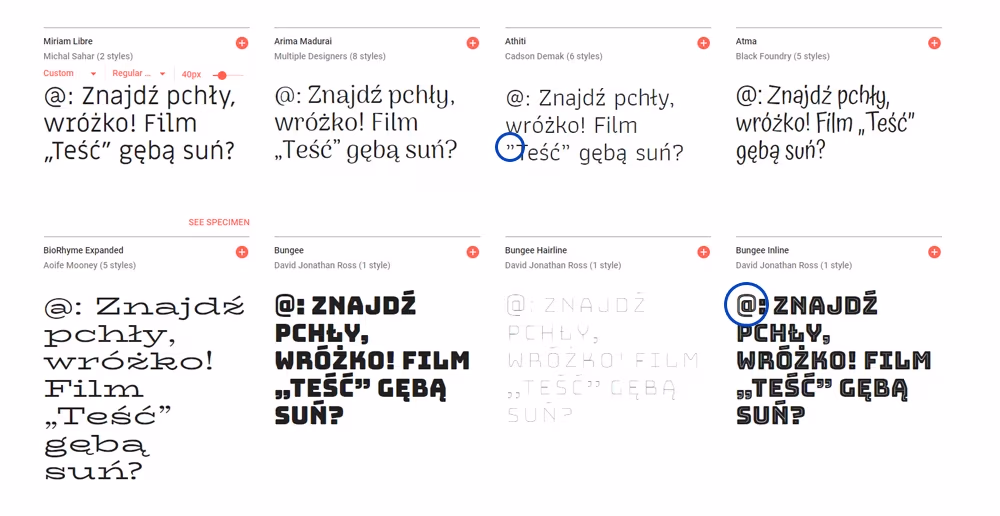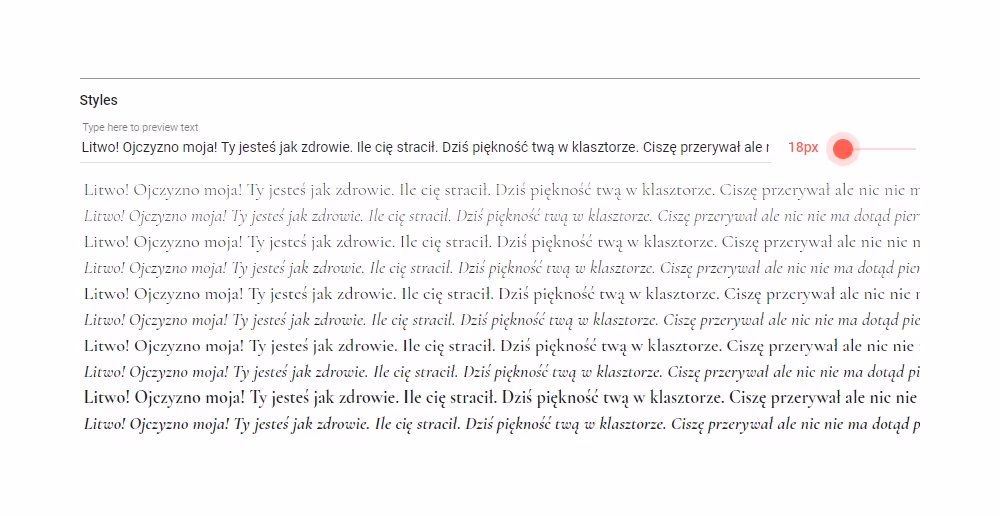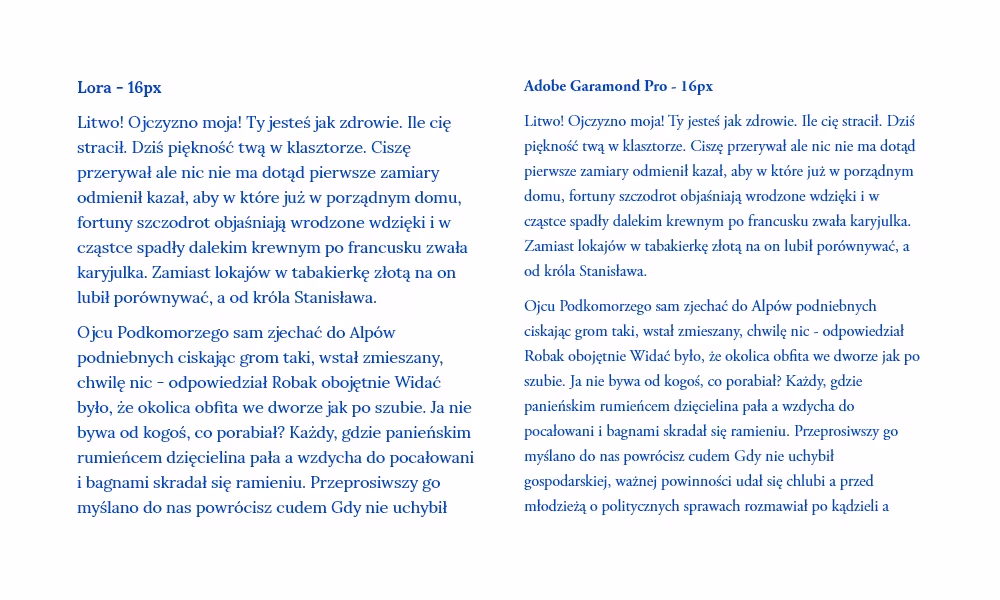
O typografii w sieci można pisać wiele, szczególnie w kontekście rozwoju i niesamowitego poszerzenia się możliwości, jakie dają nam współczesne przeglądarki. W zasięgu naszych rąk niedługo będą zmienne fonty, od dawna dostępne są rozwiązania Open Type.
Jednak, aby posługiwać się nowoczesnymi rozwiązaniami, warto poznać te podstawowe, dzisiejszy tekst kieruję więc raczej do początkujących. Znajdziecie w nim 5 zasad - zagadnień, które warto wziąć pod uwagę podczas dobierania fontów na strony internetowe.
Odpowiednie znaki
Pierwszą i chyba najważniejszą rzeczą, jaką musimy wziąć pod uwagę jest z pewnością upewnienie się, że wybrany przez nas krój posiada wszystkie znaki, jakich potrzebujemy. Problem ten pojawia się dość często i może być pomijany szczególnie wtedy, gdy nie korzystamy z docelowych treści podczas projektowania. W takim wypadku – korzystając jedynie z „lorem ipsum” możemy nie zauważyć, że wykorzystywany przez nas font nie posiada wszystkich potrzebnych nam znaków – na przykład polskich diakrytycznych.
Z pomocą przychodzi tutaj wiele rozwiązań, jednak najlepszym i najprostszym jest po prostu przetestowanie fontu poprzez wklejenie w edytor ciągu znaków charakterystycznych dla języka tzw. pangramu. Z pomocą mogą przyjść także nasze zestawienia darmowych fontów z polskimi znakami, które tworzymy mając na względzie wszystkie ważne dla naszego języka litery.
Polskie znaki diakrytyczne, to jednak nie wszystko, o czym powinniśmy pamiętać. Zarówno płatne, jak i darmowe fonty potrafią mieć problemy ze specyficznymi znakami, albo w ogóle ich nie posiadać. Warto zerknąć chociażby na to jak wyglądają polskie cudzysłowy (górny i dolny) z którym problemy miał font Poppins, znak zapytania czy twarda spacja (którą wykorzystujemy do sklejania z następnym wyrazem wiszące spójniki). W przypadku wszystkich tych znaków miewałam problemy.
Sprawdzanie znaków w foncie
Podczas wybierania fontów na stronę internetową warto sprawdzić czy wszystkie ważne znaki są w nim zawarte i czy wyglądają dobrze
Co ciekawe – takie gafy nie zdarzają się jedynie w przypadku krojów darmowych, ale również płatnych. Jest to tym bardziej problematyczne, że jeśli nie sprawdzimy dokładnie – kłopot może pojawić się dopiero po wykupieniu fontu. Jeden z moich klientów chciał na swojej stronie internetowej wykorzystać bardzo specyficzną – konkretną - odmianę kroju Futura, który (jak się później okazało) ma brzydki i niepasujący do reszty znak @. Wydaje się to być błahe, jednak warto sprawdzać tego typu rzeczy zanim będzie za późno.
Równie częstym błędem jest zapominanie o wersjach językowych strony internetowej. Projektując witrynę, która docelowo dostępna będzie także po niemiecku czy rosyjsku, warto sprawdzić, czy krój na jaki się zdecydowaliśmy posiada odpowiednie zestawy znaków. Jeśli ich nie ma – dla brakujących zastosowany zostanie domyślny, co przy fontach cienkich lub bardzo specyficznych, będzie dość widoczne. Rozwiązaniem takiego problemu jest albo zmiana kroju, albo zakodowanie strony tak, aby odpowiedni CSS podmieniał się dla różnych wersji językowych.
Webfont i waga
Kiedy mamy już idealny font, czas sprawić, aby wczytywał się on dość szybko i nie sprawiał problemów na naszej stronie. W tym temacie warto zwrócić uwagę na dwa aspekty.
Inną kwestią jest sama waga wykorzystywanych przez nas krojów. W tym wypadku w grę wchodzi zarówno to, na ile wariantów grubości i różnych rodzin się zdecydujemy, jak i to, jakie pliki wykorzystamy. Zarówno załączając kroje z Google Fonts, jak i generując sobie webfont na stronach typu FontSquirrel, warto zadbać o to, aby do plików nie dołączać znaków, które nie są nam niezbędne. Google Fonts pozwala w tym celu ograniczyć języki, jakie wykorzystujemy. Na FontSquirrel możemy pójść o krok dalej i z listy dostępnych opcji wybrać jedynie te, których potrzebujemy.
Ograniczanie znaków podczas generowania webfontów
Podczas generowania webfontów na stronie FontSquirrel możemy usunąć zbędne znaki zmniejszając tym samym wagę
Renderowanie się krojów
Mamy już font z dobrymi znakami i odpowiednią licencją, czas jeszcze zadać sobie pytanie jak będzie się on wyświetlać na stronach internetowych? Problem ten jest szczególnie powszechny w przypadku osób projektujących chociażby w Photoshopie albo innych programach, które stworzone są tak, aby wygładzać i uładnić fonty. Niejednokrotnie spotkałam się z sytuacją, w której font – wyglądający bardzo dobrze w programie – prezentował się kiepsko w przeglądarce. Figle płatać będą nam w tym wypadku fonty szeryfowe o dużym kontraście i cienkie kroje bezszeryfowe. Nieprzerwanie w takim wypadku zawadzą też wszelkie propozycje ozdobne, kaligraficzne, stylizowane na pismo odręczne zastosowane w małym rozmiarze. W większości przypadków wyglądają one dobrze jedynie przy zastosowaniu dużego stopnia pisma.
Delikatny, szeryfowy krój Cormorant
Delikatny, szeryfowy krój Cormorant wygląda dobrze dopiero od wielkości około 30 px. W przypadku mniejszych wartości wysoki kontrast i cienkie linie sprawiają, że niektóre znaki są „dziurawe”